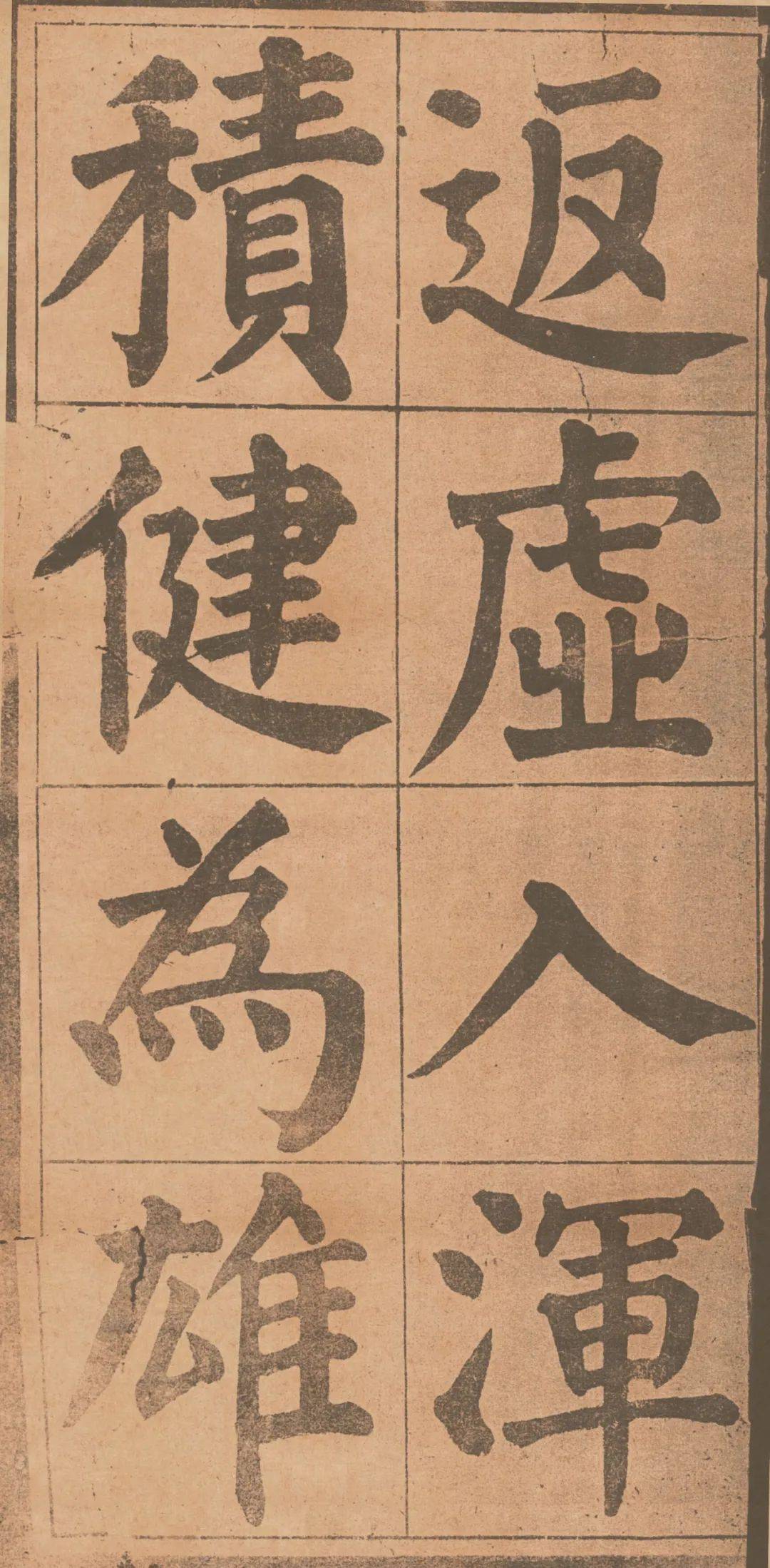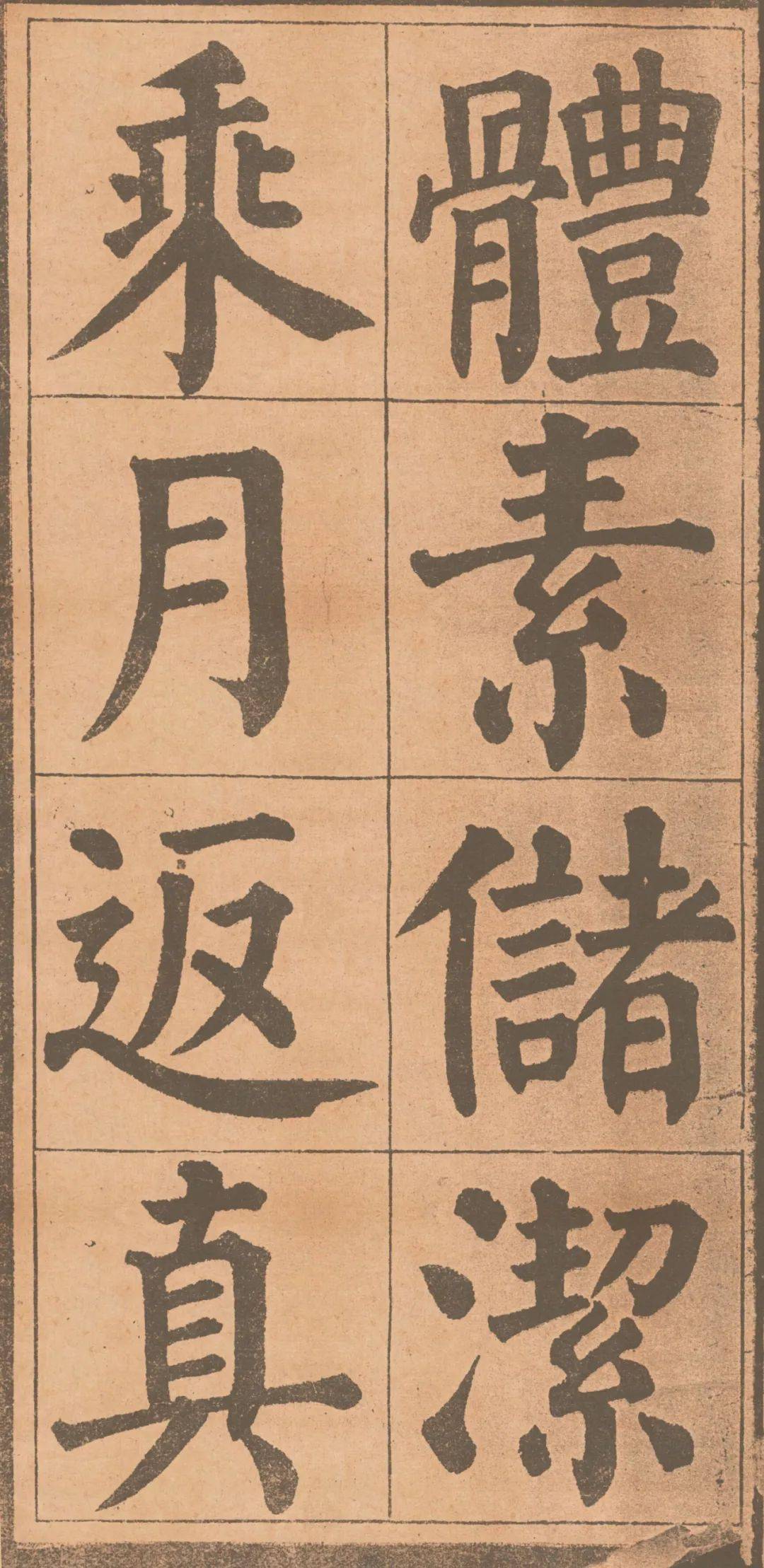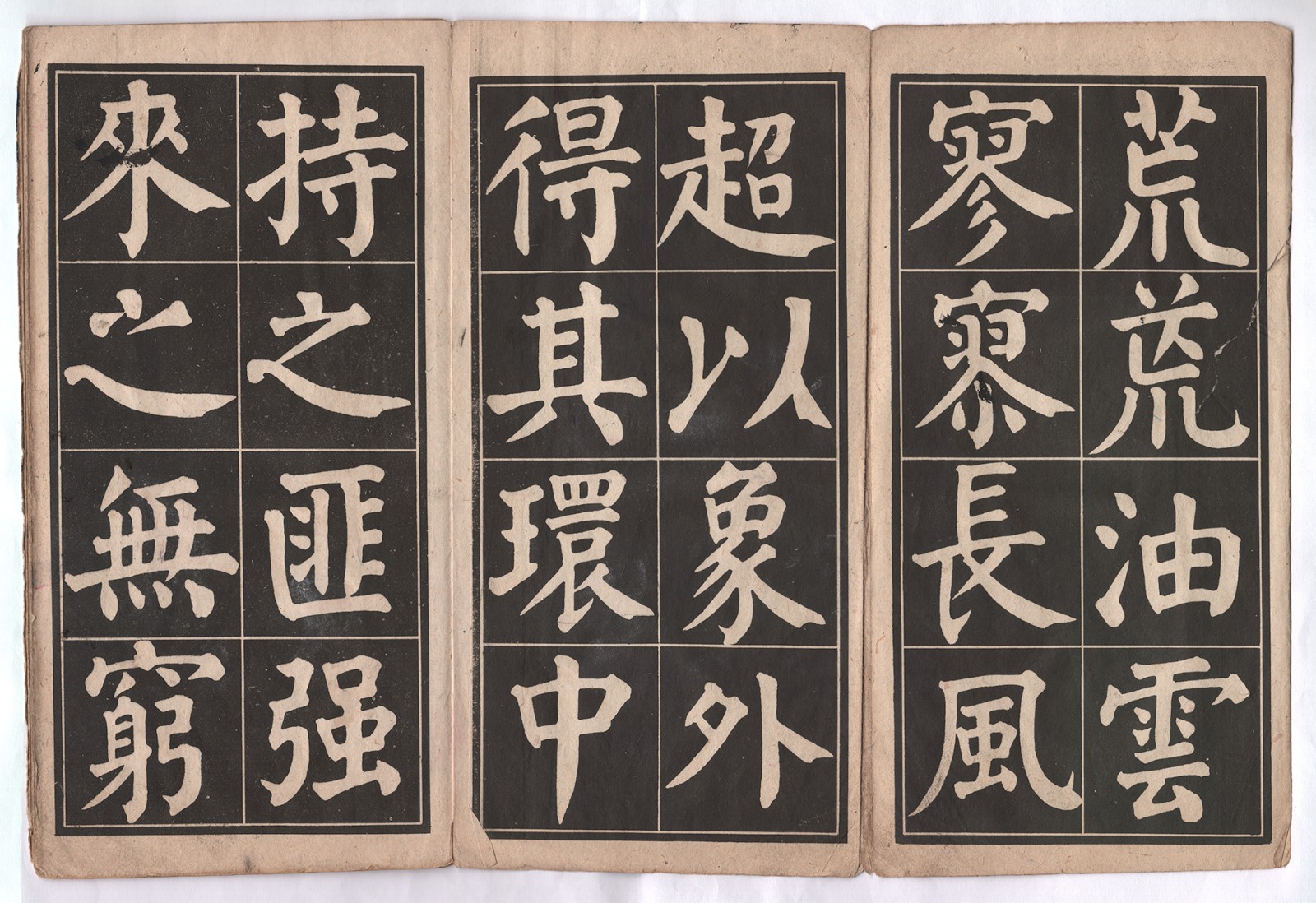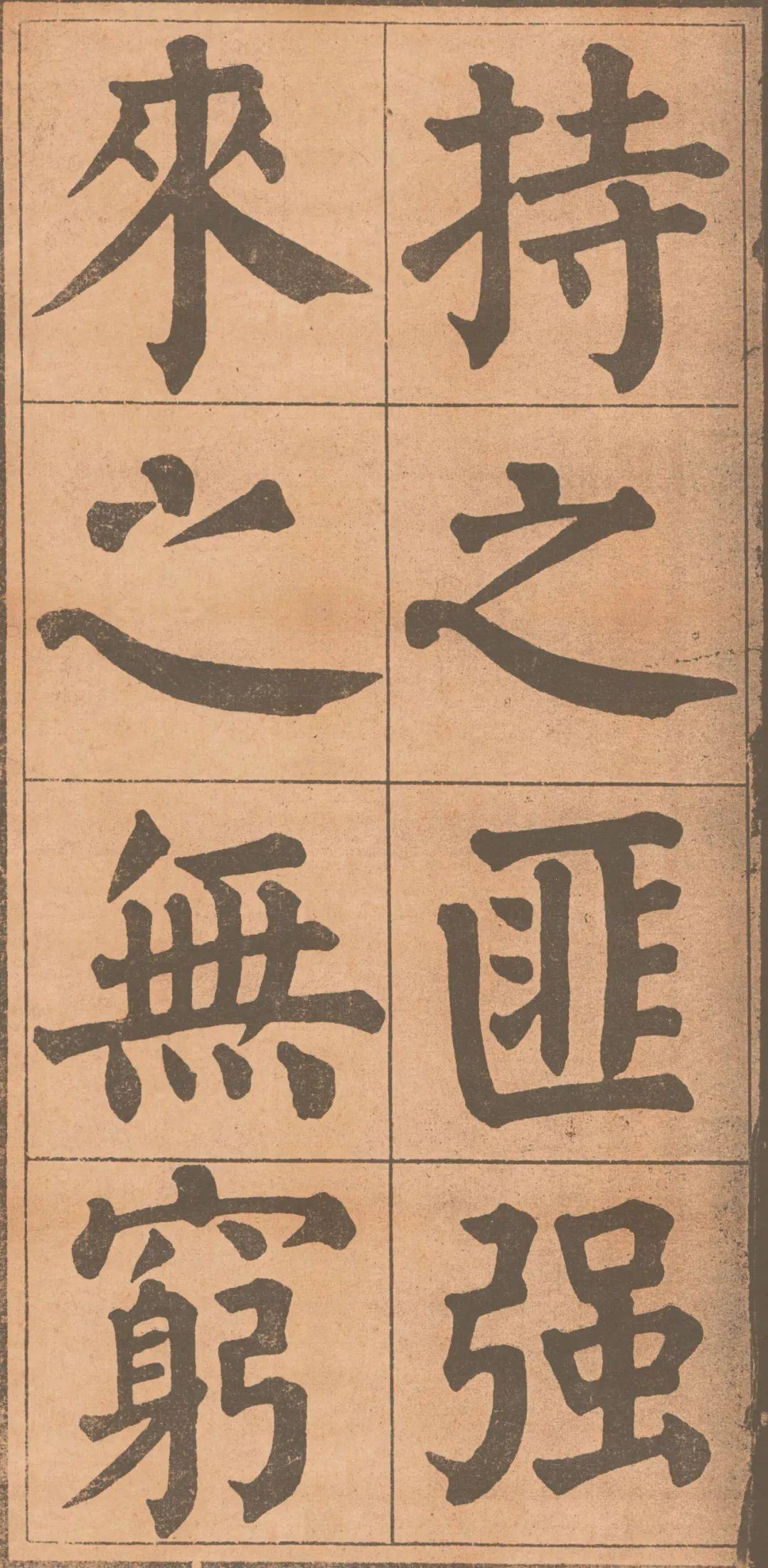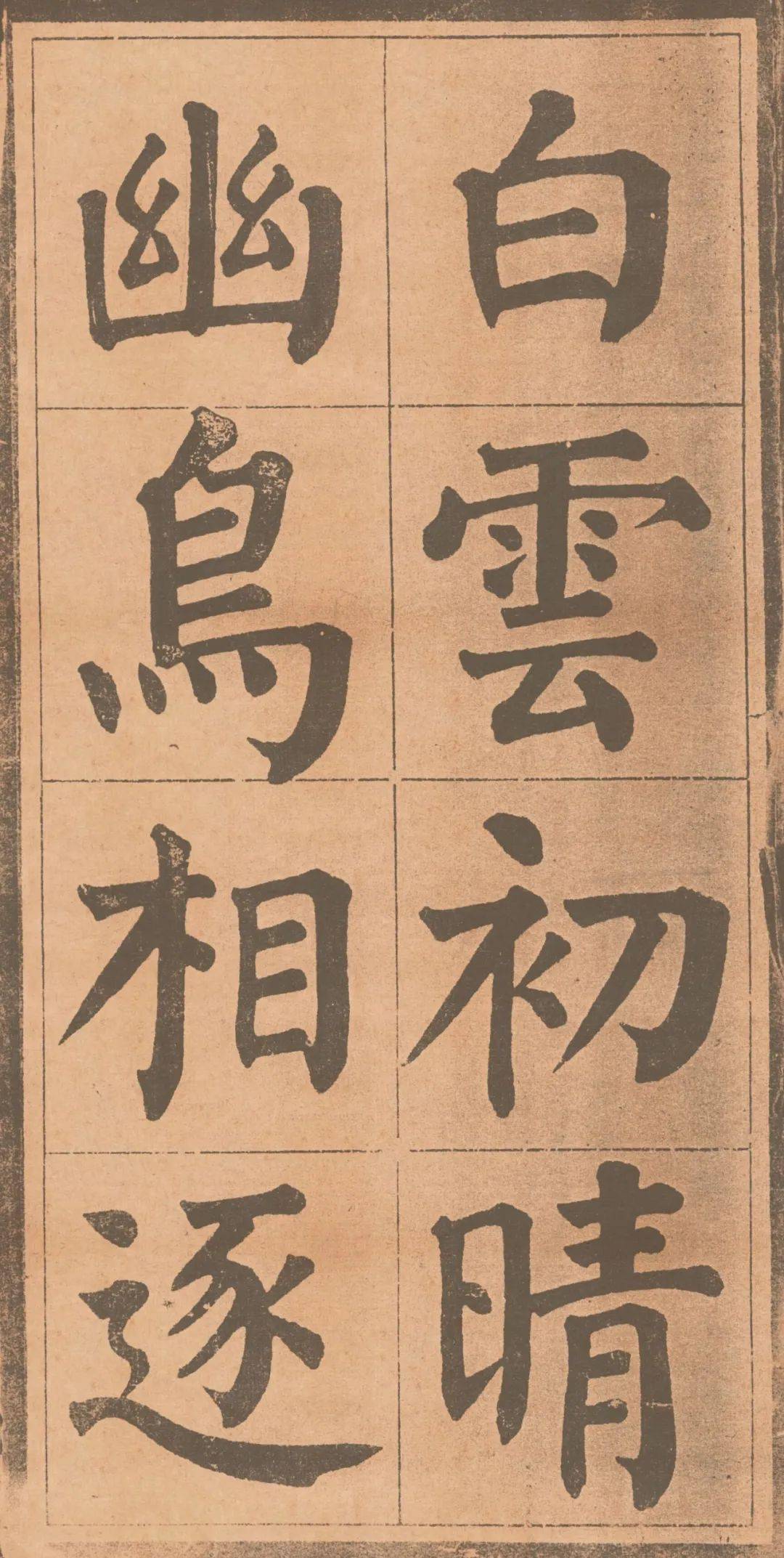
顏魯公詩品
顏魯公詩品,这款字体结构工整、笔画清晰,兼顾美观与易读性,适用于标题、正文、海报、包装、LOGO 等多种场景。字形优雅稳定,风格百搭耐看,适配日常排版与创意设计,让文字呈现更舒适、更具质感。顏魯公詩品一笔一画,皆是细节,以均衡的比例、流畅的线条打造舒适视觉体验,字形端正大气,风格简约现代。无论是商业设计、品牌宣传还是日常排版,都能轻松驾驭,让文字更有格调与力量。顏魯公詩品字体下载。
颜真卿(709年-784年8月23日),字清臣,小名羡门子,别号应方,京兆万年(今陕西省西安市)人 ,祖籍琅玡临沂(今山东省临沂市)。唐朝名臣、书法家,秘书监颜师古五世从孙、司徒颜杲卿从弟。
颜真卿书法精妙,擅长行、楷。初学褚遂良,后师从张旭,得其笔法。其正楷端庄雄伟,行书气势遒劲,创“颜体”楷书,对后世影响很大。与赵孟頫、柳公权、欧阳询并称为“楷书四大家”。又与柳公权并称“颜柳”,被称为“颜筋柳骨”。
颜真卿的真书雄秀端庄,结字由初唐的瘦长变为方形,方中见圆,具有向心力。用笔浑厚强劲,善用中锋笔法,饶有筋骨,亦有锋芒,一般横画略细,竖画、点、撇与捺略粗。这一书风,大气磅礴,多力筋骨,具有盛唐的气象。
此帖虽为后世所制颜楷习字帖《颜鲁公诗品三首》 ,但不失颜楷风采,是学习颜楷的重要字帖之一。